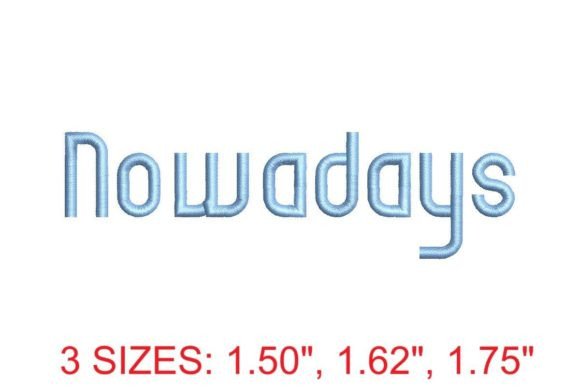
Nowadays Font
Encontrar los elementos de diseño adecuados puede ser un desafío, pero Nowadays Font ofrece una colección excepcional que eleva tu trabajo al instante.
Ya sea que estés creando productos POD (impresión bajo demanda), invitaciones de boda o gráficos para redes sociales, Nowadays Font es una opción ideal.
Consejo experto: Combina estos elementos con fuentes complementarias para crear diseños únicos y llamativos que destaquen en el mercado.